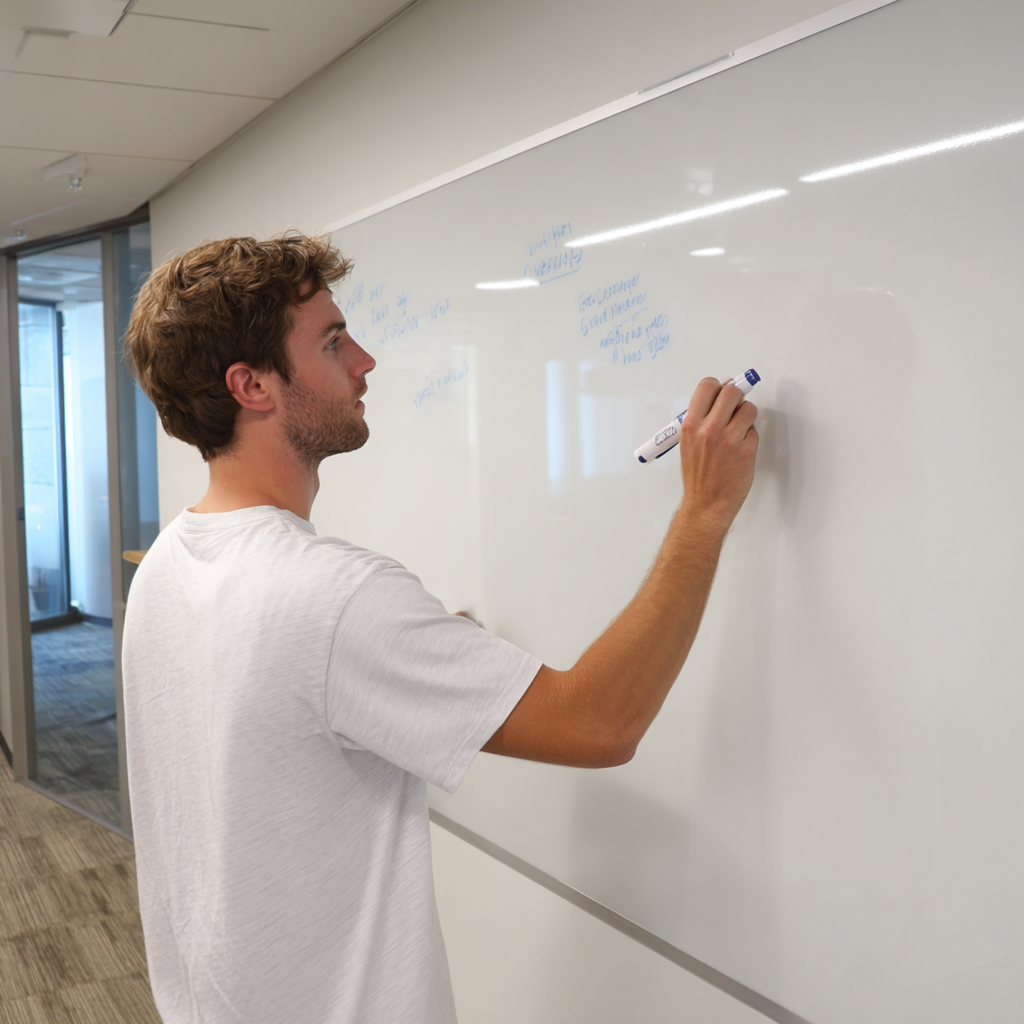
화이트보드에 판서하는 기술은 단순히 글씨를 잘 쓰는 걸 넘어, 정보를 어떻게 효과적으로 전달할 수 있느냐와 직결돼요. 발표나 강의, 회의에서 더 설득력 있게 다가가기 위해서는 화이트보드를 잘 다루는 게 정말 중요하답니다. 마커펜으로 시선을 끄는 판서를 할 수 있다면, 집중도와 이해도를 한층 더 끌어올릴 수 있어요.
제가 생각했을 때, 판서를 잘하는 사람은 ‘정보를 정리하는 능력’도 뛰어난 사람이에요. 혼자 사용하는 공간이라면 모를까, 여러 사람이 함께 보는 공간에서는 특히 글씨의 크기, 배치, 강조 등이 중요한 요소가 되거든요. 이 글에서는 누구나 쉽게 따라할 수 있는 판서 노하우를 알려드릴게요.
그럼 이제, 본격적으로 화이트보드 판서의 모든 것을 하나하나 정리해서 살펴볼까요? 아마 글을 다 읽고 나면, 바로 마커펜을 들고 연습해보고 싶어질 거예요!✍️
📌 화이트보드 판서의 중요성
화이트보드는 단순한 필기 도구를 넘어서, 발표자와 청중 사이의 소통을 매끄럽게 해주는 시각적 도구예요. 특히 회의실, 강의실, 스터디 모임 등 다양한 상황에서 빠르게 아이디어를 전달하고 피드백을 주고받을 수 있는 장점이 있어요. 화이트보드를 잘 활용하면 복잡한 개념도 시각적으로 쉽게 정리할 수 있어서 이해도를 높여주죠.
교육 현장에서는 화이트보드 판서를 통해 학생들의 집중력을 끌어올릴 수 있어요. 판서의 방향, 구성, 색상 사용에 따라 학생들이 내용을 얼마나 오래 기억하느냐도 달라진답니다. 특히 수학, 과학처럼 단계적 설명이 필요한 과목에서 판서의 흐름이 논리 구조를 효과적으로 보여주는 역할을 해요.
업무 회의나 프레젠테이션에서도 마찬가지예요. 누군가가 설명을 하는 중일 때, 말로만 설명하는 것보다 화이트보드에 직접 구조를 그려가며 진행하면 훨씬 설득력 있고 명확한 전달이 가능해요. 참여자들이 내용을 함께 시각화하며 이해하니까 더 생산적인 회의가 될 수 있어요.
그리고 무엇보다 큰 장점은, 수정이 쉽다는 점이에요. 실수하더라도 바로 지우고 다시 작성할 수 있어서 부담이 적고, 반복 학습과 피드백에도 유리하죠. 발표 중간에 누군가 질문을 하더라도 보드에 추가적으로 내용을 적거나 흐름을 조정하기가 편해요.
결국 화이트보드 판서를 잘한다는 건, 단순히 보기 좋게 글씨를 쓰는 기술이 아니라 정보의 흐름을 설계하고, 상대방의 이해를 고려해 가시화하는 능력과 연결돼요. 이런 점에서 볼 때, 판서는 커뮤니케이션의 핵심 도구라고도 할 수 있어요.🎯
또한 많은 발표자들이 화이트보드를 활용할 때 가장 고민하는 건 ‘어떻게 하면 더 보기 좋게 쓸 수 있을까?’라는 점인데요. 이런 고민을 해결하기 위해선 기본적인 판서 원칙과 팁들을 익히는 게 정말 도움이 돼요.
이제 본격적으로 화이트보드 마커펜을 사용할 때 어떤 도구가 필요한지, 어떤 순서로 글을 구성해야 하는지, 실제로 어떻게 쓰면 좋을지 하나씩 배워볼게요! ✨
📊 화이트보드 활용 목적별 비교표
활용 목적 설명 방식 주요 포인트 추천 스타일 강의 순차적 설명 단계별 정리 왼→오른쪽 구성 회의 아이디어 도식화 구조 시각화 중앙 중심 배치 워크숍 참여형 구성 토의 공간 확보 여백 활용 스터디 키워드 중심 핵심 개념 정리 컬러코드 사용 이 표를 참고하면, 상황에 따라 어떤 방식으로 판서를 구성할지 감이 딱 잡힐 거예요. 그럼 다음으로는 마커펜과 도구 선택법을 알아볼게요!✍️
🖊️ 필요한 마커와 도구
화이트보드 판서를 제대로 하려면 도구부터 제대로 갖추는 게 중요해요. 가장 기본이 되는 건 당연히 마커펜인데요, 마커의 굵기, 색상, 잉크 흐름 상태에 따라 판서의 가독성과 전달력이 크게 달라지죠. 얇은 마커는 정밀한 글씨에 좋고, 두꺼운 마커는 제목이나 강조에 유리해요. 상황에 맞는 굵기 선택이 핵심이에요.
컬러 마커도 꼭 준비하는 게 좋아요. 보통 검정, 파랑, 빨강, 초록 네 가지는 기본이에요. 검정은 본문, 파랑은 보조 정보, 빨강은 강조, 초록은 예시나 연결선 등으로 활용하면 보는 사람 입장에서 훨씬 직관적으로 받아들일 수 있답니다. 색깔마다 역할을 정해두고 쓰는 습관을 들이면 좋아요.
마커펜 외에도 화이트보드 지우개나 전용 천도 중요해요. 마커를 지울 때 자국이 남거나 번지지 않도록 잘 관리해야 하거든요. 특히 오래된 마커 자국을 없애려면 화이트보드 클리너 스프레이나 알코올 솜을 준비하는 것도 좋은 방법이에요. 깔끔한 보드는 곧 깔끔한 발표와 직결되니까요!
화이트보드에 선을 그릴 일이 많다면 자나 화살표 템플릿을 활용하는 것도 좋아요. 특히 도식이나 흐름도 그릴 때 직선, 곡선, 대각선 등을 정돈되게 표현하면 시각적인 인상이 훨씬 좋아져요. 보드가 크다면 레이저 포인터도 좋은 도구가 될 수 있어요. 멀리 있는 청중에게 특정 위치를 정확히 가리킬 수 있거든요.
마지막으로, 정전기 방지 스프레이를 사용하는 것도 고려해볼 만해요. 먼지가 잘 붙지 않고, 글씨 번짐도 줄여줘서 보드의 상태를 유지하는 데 효과적이랍니다. 어떤 도구를 준비하느냐에 따라 판서의 질이 달라진다고 해도 과언이 아니에요.🧼
요약하자면, 단순히 마커 하나 들고 시작하는 게 아니라 상황에 맞는 색상, 굵기, 지우개, 보조도구까지 미리 준비해두는 게 중요하다는 거예요. 그럼 아래 표로 어떤 마커와 도구가 필요한지 정리해볼게요!📋
도구가 제대로 갖춰지면, 다음 단계인 판서의 구조 설계가 한결 쉬워져요. 그럼 이제 다음 섹션에서 기본적인 판서 구성을 배워볼게요! 😎
🖍️ 마커 및 도구별 특징 비교표
도구 설명 추천 용도 비고 검정 마커 (굵은 팁) 메인 텍스트용 제목/중요 내용 가독성 우수 파랑 마커 (얇은 팁) 보조 내용 작성 부가 설명 시각적 구분 용이 빨강 마커 강조 포인트 핵심 단어 과다 사용은 피해야 함 화이트보드 지우개 마커 제거용 정기적 청소 지속적인 관리 필요 클리너/스프레이 오래된 자국 제거 보드 상태 유지 보조도구와 함께 사용 이제 필요한 마커와 도구들을 제대로 이해했으니, 다음 섹션에서는 이 도구들을 활용한 효과적인 판서 구성 방법을 알아볼게요. 구조만 잘 잡아도 절반은 성공이랍니다!📐
📐 판서의 기본 구조 만들기
화이트보드 판서를 할 때 가장 먼저 해야 할 일은 '어디서부터 어떻게 채울지'를 계획하는 거예요. 무작정 쓰기 시작하면 공간 배분이 어긋나고, 중간에 여백이 부족해서 지우고 다시 쓰는 상황이 생기기 쉬워요. 그래서 사전에 '전체 흐름'을 머릿속으로 한 번 정리해보는 게 좋아요.
기본적인 판서 구조는 '좌측 상단 → 우측 하단' 방향으로 흐르는 게 좋아요. 시선이 자연스럽게 따라갈 수 있도록 구성하는 거죠. 특히 첫 번째 줄에는 제목 또는 큰 주제를 쓰고, 그 아래엔 세부 내용을 단계적으로 써내려가는 방식이 가장 직관적이에요. 이렇게 하면 보는 사람 입장에서 이해하기 쉽고, 흐름을 잡기도 편하답니다.
보드 전체를 3등분 해서 상단은 제목, 중단은 본론, 하단은 요약이나 결론으로 나누는 방법도 좋아요. 마치 PPT 슬라이드처럼 생각하면 돼요. 주제별로 구역을 나누면 시각적으로도 정돈돼 보이고, 설명 중간에 복습하거나 강조할 부분을 다시 돌아가기도 쉬워요.
포스트잇이나 연습 종이에 먼저 초안을 그려보는 것도 좋은 방법이에요. 큰 흐름, 핵심 키워드, 연결선 등을 미리 설계하면 실제 판서할 때 훨씬 빠르고 안정감 있게 쓸 수 있어요. 그리고 같은 색상의 마커를 반복 사용하면 가독성이 떨어지기 때문에 섹션마다 컬러를 다르게 설정해두는 것도 팁이에요.
또 중요한 건 ‘빈 공간’이에요. 화이트보드를 꽉 채우려고만 하면 오히려 지저분해 보여요. 여백을 의도적으로 남겨두고, 필요한 순간에 추가 설명이나 예시를 쓰는 식으로 유연하게 활용하는 게 더 효과적이에요. ‘덜 채우는 용기’도 좋은 판서의 비결이죠.🧠
시작 위치도 항상 동일하게 유지하는 게 좋아요. 예를 들어, 항상 왼쪽 상단에서 시작한다면 보는 사람의 시선도 익숙해지고 내용 파악이 쉬워져요. 반대로 순서 없이 여기저기 쓰면 혼란스럽고 집중이 흐트러질 수 있어요. 규칙적인 레이아웃이 아주 중요한 포인트예요.
간단한 도식이나 화살표를 곁들이는 것도 추천해요. 글만 가득한 보드보다는, 정보 간의 관계를 시각화해주는 것이 훨씬 설득력 있어요. 특히 수업이나 프레젠테이션에서는 이런 비주얼 요소가 전달력을 높여주는 강력한 무기가 돼요.📊
📏 판서 구조 설계 체크리스트
항목 설명 활용 팁 시작 위치 좌측 상단 고정 시선 유도에 효과적 세로 구성 위 → 아래 순 논리 흐름 강조 여백 적절한 공간 확보 추가 설명 가능 구획 나누기 상/중/하 구역화 내용 정리 쉬움 색상 활용 섹션별 구분 가독성 향상 여기까지가 기본적인 판서 구조 만드는 방법이에요. 다음 섹션에서는 이 구조를 바탕으로 글씨를 더 예쁘고 보기 좋게 쓰는 실제 팁들을 알려드릴게요!✍️
💡 깔끔하게 쓰는 팁
판서에서 가장 중요한 건 바로 ‘가독성’이에요. 아무리 좋은 내용을 쓰더라도 글씨가 삐뚤빼뚤하거나 너무 작고 복잡하면 전달력이 뚝 떨어지거든요. 먼저 글씨 크기는 멀리서도 잘 보일 정도로 충분히 크게 써야 해요. 최소 5미터 거리에서도 또렷하게 보이도록 적당한 굵기로 쓰는 게 좋아요.
한 글자, 한 글자를 또박또박 일정한 간격으로 쓰는 것도 중요해요. 특히 한 줄에 너무 많은 글자를 몰아넣지 말고, 문장을 짧게 나누어서 적는 게 훨씬 깔끔하게 보여요. 글씨체는 자신의 손글씨 스타일을 유지하되, ‘ㅇ’이나 ‘ㅁ’처럼 닫힌 글자는 꽉 채우고, ‘ㅣ’, ‘ㅡ’는 수평 수직을 의식적으로 맞춰보면 전체적인 균형이 좋아져요.
글자의 줄간격도 중요해요. 위줄과 아래줄이 너무 가까우면 판서가 답답하게 보이고, 어디서 끊어 읽어야 할지 헷갈리게 만들어요. 줄과 줄 사이에는 손가락 한 마디 정도의 여백을 두는 게 좋고, 단락 간 간격은 더 넉넉하게 둬야 보기 좋아요. 마치 종이에 단락 나누듯이요!
중요한 단어나 개념은 색상 마커로 강조하거나 박스를 쳐주는 방식으로 구분해줘야 해요. 단, 모든 걸 강조하면 아무 것도 강조되지 않기 때문에 정말 핵심만 골라서! 그리고 마커를 사용할 땐 너무 빨리 쓰지 말고, 천천히 써야 잉크 번짐 없이 선명하게 남아요. 특히 색상 마커는 천천히 써야 컬러가 살아나요.🌈
Q5. 화이트보드 글씨가 잘 안 지워질 땐 어떻게 해요?
A5. 전용 화이트보드 클리너나 알코올 솜을 이용하면 쉽게 제거돼요. 오래된 흔적은 마른 마커로 덧그린 후 바로 지우는 방식도 효과적이에요.
Q6. 발표 중 판서 흐름이 꼬이면 어떻게 해야 하나요?
A6. 흐름이 꼬였을 땐 당황하지 말고, 보드 하단에 '정리 섹션'을 만들어 다시 구조화해주는 것도 좋은 방법이에요. 중간 요약도 효과 있어요.
Q7. 전자칠판이나 디지털 화이트보드에서도 이 팁이 통하나요?
A7. 물론이죠! 흐름 설계, 색상 분배, 구조적 배치는 디지털 판서에도 그대로 적용돼요. 다만, 터치 민감도나 해상도에 따라 선명도 차이는 있어요.
Q8. 가장 빠르게 판서 실력을 높일 수 있는 방법은?
A8. 자주 쓰는 문장, 틀, 도식 등을 '템플릿'처럼 정해놓고 연습하는 거예요. 자주 반복하면서 나만의 루틴을 만드는 게 가장 빠른 길이에요.